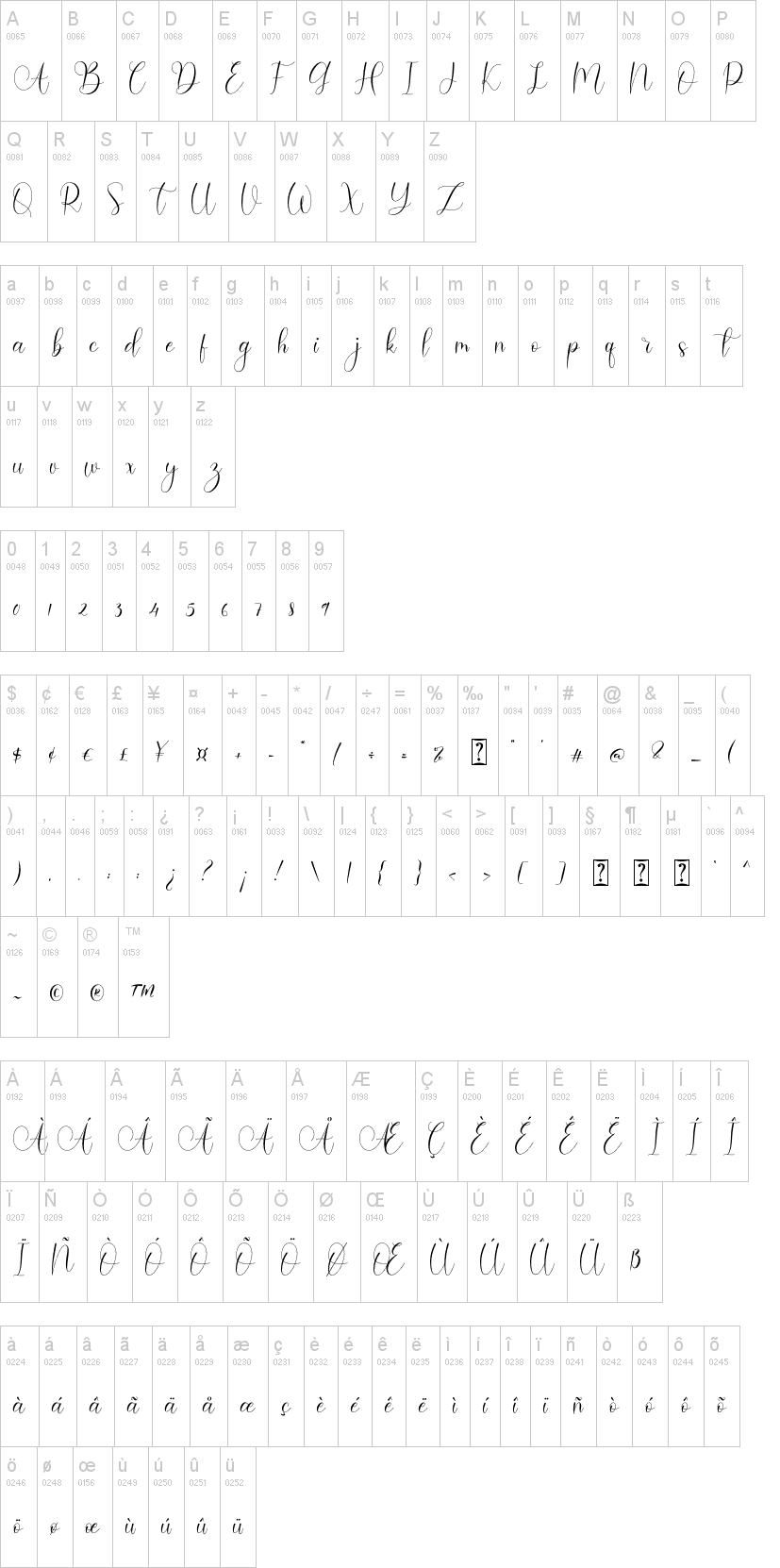
Amadea
Amadea 字体是一款简洁、现代的多语言字体,由设计师 Andriy Konstantynov 创作。Amadea 字体以现代、简洁的设计为特色,具有良好的可读性,适用于各种多语言场景,如文章、标题、标签等。它支持多种英文字符,包括大小写字母、数字、符号、标点等,还支持多种非拉丁语言,如俄语、希腊语、土耳其语等。
Amadea是一款非常不错的手写艺术字体,具有很好的视觉感,适合于文化类的宣传设计、商业类品牌的广告和产品包装设计以及个性化文字排版等较多场景。